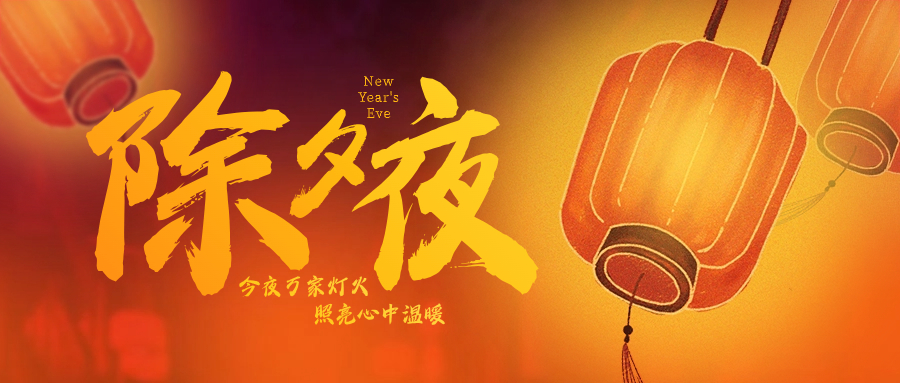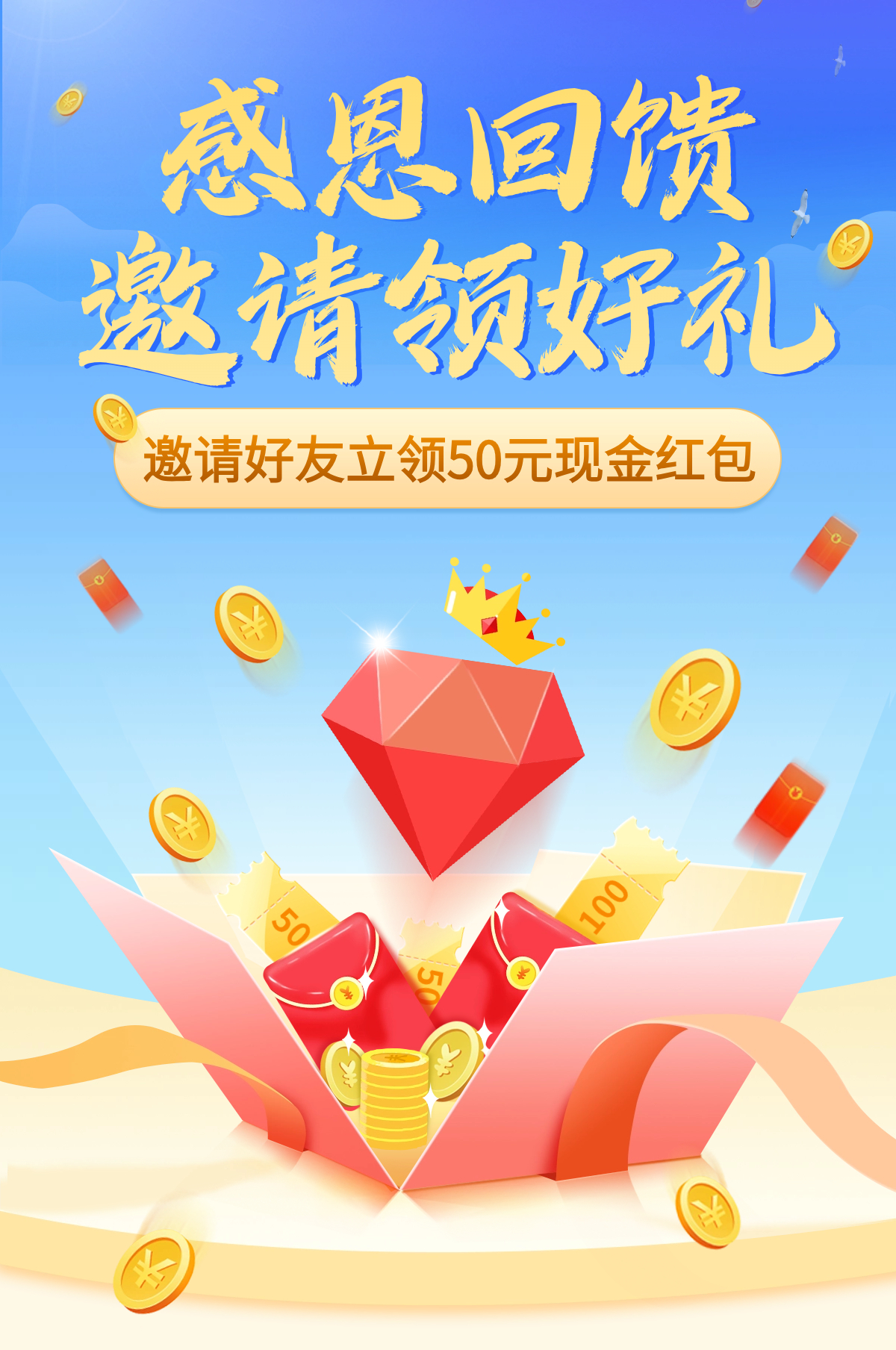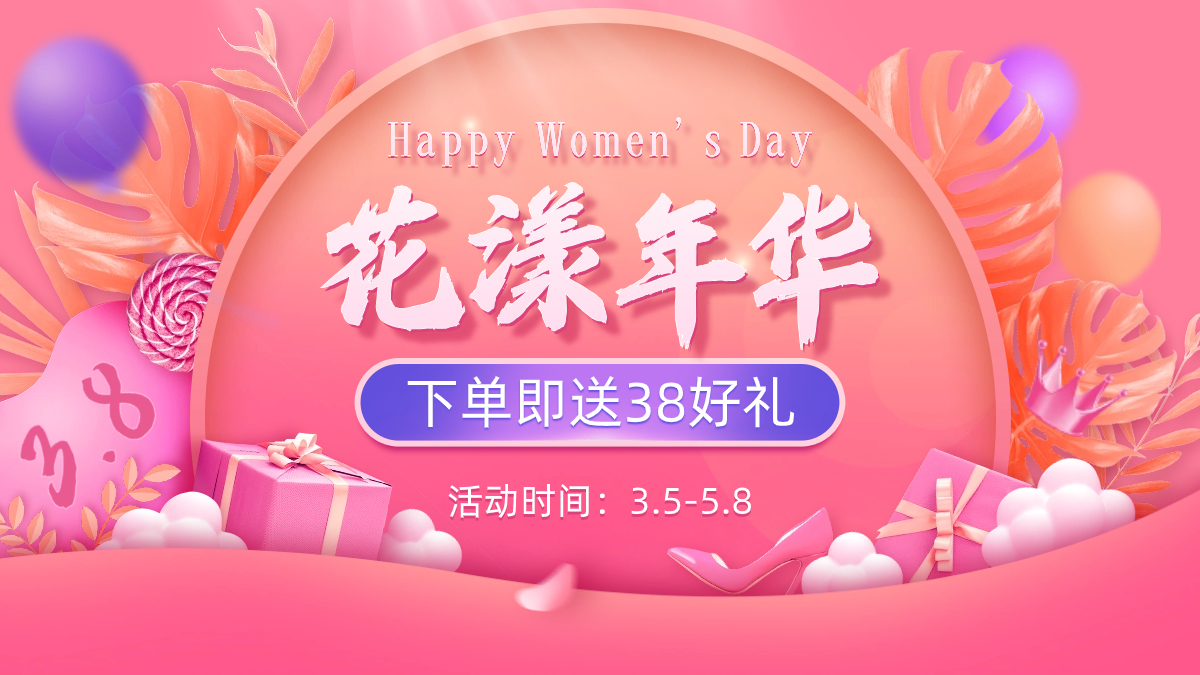
兵克逍遥体
兵克逍遥体,兵克逍遥体,其笔力坚实如磐石,气势昂扬如破竹,笔触狂放。字形浑厚而洒脱,既有山川之雄浑,又有江河之奔腾,每一笔每一划都如同力士挥拳,坚实有力,直击人心,在视觉上呈现出一种强烈的冲击力与感染力,为人们带来视觉与心灵的双重享受。适合于电影海报、包装、品牌名称、各类商业海报、户外广告标题等。